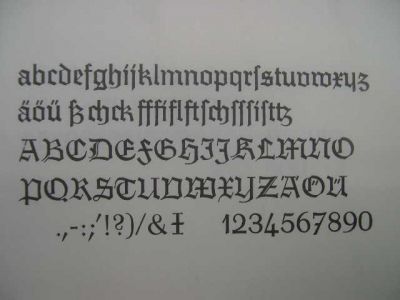
»Trump Deutsch« dringend gesucht.
nach langem Einlesen klinke ich mich jetzt einmal in das TypoForum ein,
und zwar gleich mit einer Frage:
Weiß jemand von euch, ob es Georg Trumps »Trump Deutsch« in einer (guten)
digitalen Fassung gibt?
Ich habe über Google und die gängigen Font-Suchmaschinen nur die Halbfette gefunden, und zwar (finde ich) in
einer ziemlich schlecht digitalisierten Version.
Es wäre super, wenn jemand Rat wüsste!
Dann hast Du die von Steffmann gefunden?
Ich kenne sie nicht aus eigener Anwendung, aber ich dachte, seine Schriften wären gut?
Hallo Georg,
ja, das ist genau der Font, den ich gefunden habe.
Mit der Fetten kann ich aber leider nichts anfangen :(
Ich brauche die Schrift nur, um ein kurzes Wort (in 6-8pt) darin zu setzen;
und wenn ich mir die Mühe, aus »Vita Activa« die entsprechenden Zeichen zu scannen und zu vektorisieren sparen könnte,
wäre das doch nichts verkehrtes.
Hier mal ein Screenshot von »schwammigen Stellen«:
Ich muss dazu sagen, dass ich auch nur Laie bin, was die Beurteilung
von Schriften angeht, aber ich finde die Formen ziemlich plump und mit unnötig vielen Ankerpunkten nachgezeichnet.
...und es ist auch noch eine Berthold-Schrift.
Ich befürchte, da wirst Du keine magere Version finden.
Erstaunlich genug, daß es diese fette gibt.
Du könntest Deine Frage einmal ins Type ID Board von Typophile einstellen:
Dort habe ich schon Antworten auf Fragen nach Schriften bekommen, auf die ich schon gar nicht mehr gehofft hatte.
Probier es mal bei Markwart Lindenthal unter http://www.fraktur.de. Dort gibt es auf jedenfall die magere Trump Deutsch … aber nur in der F-Tastaturbelegung nach Vorlage des Original-Fonts
Leider nein. Fast alle Schriften von Steffmann sind sehr „weich“ und ein bisschen unscharf im Gegensatz zu den Helzelschriften z.B. oder eben auch den Schriften von der FVL-GbR.
Auf Fraktur.de heißt es dazu: „mit „Steffmann“ gekennzeichnete Schriften stellt Herr Dieter Steffmann allen privaten Nutzern im PS-Fonts-Format kostenfrei zur Verfügung. Diese Schriften eignen sich aufgrund ihrer zum Teil wenig sorgfältigen Ausformung und der oft mangelnden Vollständigkeit nicht für professionellen Einsatz. Für private Briefe und ähnliche Aufgaben dürften sie vollauf genügen. Bei höheren Ansprüchen, insbesondere auch für größere Schriftgrade empfehlen wir die Anschaffung der Original-Schriften…“
Also
Die Steffmann-Schriften fallen sehr unterschiedlich aus. Die wunderschöne Walbaum-Fraktur z.B. ist gut und mit ordentlich geputzter Umrisslinie ausgeführt, andere sind wohl aus automatisch vektorisierten Scans entstanden, was man ihnen leider auch ansieht.
Eine Frage an die alten Bleisetzer unter euch:
Hat die Trump Deutsch (bzw. ihre Schnitte) eine Namensänderung hinter sich?
Das, was auf Georgs Seite und von Steffmann "Fette Trump Deutsch" genannt wird, heißt in Vita Activa nur "Trump Deutsch",
und der 'regular-Schnitt', nach dem wir hier forschen,
heißt "Magere Trump Deutsch".
Irgendwann muss sich also ein "Fett" vor den Namen gestohlen haben.
Aber wann, und wo, und weshalb überhaupt?!
Das ist eine ziemlich verwirrende Angelegenheit :?
Dies ist nur mein subjektiver Eindruck:
Zunächst ein Faktum:
Ich selbst klassifizieren meine Bleisatz-Schriften selbstverständlich nach den Original-Namen. Die stehen in den entsprechenden Original-Hauptproben bzw. im "Verzeichnis der Schriftennamen" vom Verein der Schriftgießereien von 1950. Die Einträge dort legten die Namensrechte fest, also sind sie zutreffend:
Aber wieso weicht die Namensgebung in Vita Activa von der aus dem Verzeichnis ab?
Vita Activa kennt nur "Trump Deutsch" und "magere Trump Deutsch".
Eine von beiden Publikationen ist also im Unrecht.
Kannst du noch einmal in dem Verzeichnis nachsehen?
im Namensverzeichnis wird nur die Trump-Deutsch gelistet.
Aber ich habe in Georg Kandlers Erinnerungen an den Bleisatz, Teil 2, ein komplettes Schriftmuster der Trump-Deutsch, Magere gefunden. Die Quelle ist sehr zuverlässig.